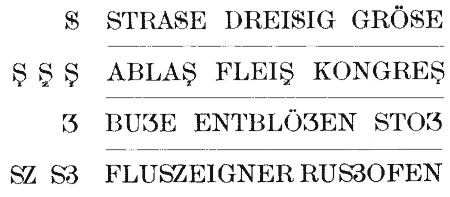
[Mitglied b750…] Geschrieben März 8, 2003 Teilen Geschrieben März 8, 2003 Folgendes erreichte mich per Mail. Ich denke, das ist ein interessanten Diskussionsthema, das vielleicht auch andere interessiert: Hallo Herr Herrmann, ich habe vor einiger Zeit ihr Typotutorial über die richtige Verwendung des Eszett gelesen und es sprach mir geradezu aus der Seele. Leider entdecke ich sehr oft peinliche ß-Fehler im Alltag. Vor einigen Monaten erblickte ich im Supermarkt den Grießpudding eines regionalen Milchproduktherstellers. Die Verpackung war durchaus schön gestaltet, doch war das Wort Grießpudding komplett in Versalien gesetzt mit einem ß an fünfter Stelle! Zu Hause angekommen schrieb ich der Marketingabteilung des Unternehmens eine ausführliche Mail mit Verweis auf den relevanten Absatz im Duden. Einige Wochen später erhielt ich zu meiner eigenen Verwunderung tatsächlich eine Antwort. Die verantwortliche Dame erklärte mir, dass sie dies Problem ausführlich intern diskutiert habe und dabei auch auf weitere Fehler auf den Produktverpackungen ihres Hauses aufmerksam wurde. Jedoch wäre eine sofortige Korrektur der Verpackungen aus Kostengründen leider nicht zu realisieren. Am Ende dankte sie mir für meine Aufmerksamkeit und war erstmal zufrieden … mal schauen wie lange die Änderung der Verpackung auf sich warten lässt. :) Durch Zufall stieß ich letztens auf einen alten DDR-Duden aus dem Jahre 1962, auf dessen Titel folgendes zu lesen ist: »DER GROßE DUDEN RECHTSCHREIBUNG«. Ich war für einige Sekunden absolut sprachlos und habe sogleich ein Beweisfoto geschossen und an diese Mail angehängt. Vielleicht lässt sich ja mit ein wenig Aufwand die Ursache für diesen peinlichen Faux Pas ausfindig machen … Im Kapitel »Rechtschreibung der Laute« steht zum Thema Eszett u.a. folgendes: »Das Zeichen ß fehlt leider noch als Großbuchstabe. Bemühungen, es zu schaffen, sind im Gange. Es wird jetzt noch ersetzt durch SS oder, falls Mißverständnisse möglich sind, durch SZ.« Ist die Frage warum es auf dem Titel dann defitiv falsch geschrieben ist. Gab es tatsächlich Bemühungen eine Ligatur für die Versalien zu schaffen? Als ich das las, war ich sehr fasziniert von dem Gedanken eines großen Eszetts. Ich werde versuchen mich im neuen Semester meines Designstudiums dem Thema anzunehmen, mal schauen was mein Typo-Prof. zum Thema sagt. Zum einen möchte ich herausfinden ob es tatsächlich Bemühungen dieses Art gab, wenn ja wie weit sie fortgeschritten waren und warum bis heute keine Ligatur der Versalien S und Z existiert. Zudem würde ich gern eigene Gestaltungsmöglichkeiten großer Eszetts bekannter Schriften kreieren. Ich würde mich sehr über eine Antwort von Ihnen freuen! Viele Grüße! Martin Jordan Link zu diesem Kommentar
[Mitglied b750…] Geschrieben März 8, 2003 Teilen Geschrieben März 8, 2003 Dass es Bemühungen gab, ein "großes Eszett" zu etablieren, ist mir auch neu. Aber mag ja sein, dass es in der DDR diese Bemühungen gab, diese dann aber mit der Wende nicht weiter verfolgt wurden. Schließlich gibt es ja auch keinen "DDR-Duden" mehr. Aber wozu brauchen wir ein großes Eszett? In der deutschen Rechtschreibung gibt es kein einziges Wort, das mit einem Eszett beginnt. Also gibt es auch keine Notwendigkeit für ein großes Eszett. Und nur für den Versalsatz ein solches zu schaffen? Ich finde es falsch, einen Buchstaben in unser Alphabet einzusetzen, wenn es dafür keine rechtschreiberische Notwendigkeit gibt oder wenn er nur in Ausnahmen eingesetzt wird (und der Versalsatz ist ja eine typografische Ausnahme, die man nur in Überschriften und Hervorhebungen einsetzt). Wenn jemand gerne ausschließlich Versalien verwenden möchte und ein Eszett drin vorkommt, muss er sich halt mit einem Doppel-S behelfen. Das ist ja auch keine Katastrophe. Denis Link zu diesem Kommentar
[Mitglied b750…] Geschrieben März 10, 2003 Teilen Geschrieben März 10, 2003 Meines Wissens ist das "ß" kein Buchstabe, sondern eine Ligatur aus "s" und "z" und kann somit schwerlich ... äh ... kapitalisiert werden. Nicht, dass es unmöglich wäre, aber nicht ganz einfach, sicherlich. :) http://www.carb.de Link zu diesem Kommentar
[Mitglied b750…] Geschrieben März 10, 2003 Teilen Geschrieben März 10, 2003 Sicher ist das Eszett eine Ligatur aus zwei Kleinbuchstaben. Aber es existieren doch durchaus auch Ligaturen bestehend aus zwei Versalbuchstaben. Was spricht also dagegen im Rahmen eines Semesterprojekts einfach mal nach jenen alten Entwürfen zu recherchieren und dann ein wenig zu experimentieren? Es werden meiner Meinung nach weitaus sinnlosere Projekte an unseren Hochschulen für Gestaltung durchgeführt und unterstützt … dass das dabei eventuell herauskommende Zeichen NICHT von der Öffentlichkeit als großes Eszett akzeptiert wird und am Ende zum Einsatz kommt ist mir durchaus klar. Dennoch bin ich einfach unglaublich neugierig, was dort vor 40 Jahren in Köpfen der ostdeutschen Typographen ausgedacht worden ist. Vielleicht sind ja sehr spannende Ansätze für die Kreation ein komplett neues Buchstabens dabei … vielleicht sind aber die Ideen auch längst mit ihren Schöpfern begraben. Ich möchte es herausfinden … für mich. Gruß. Martin Jordan. Link zu diesem Kommentar
[Mitglied b750…] Geschrieben März 10, 2003 Teilen Geschrieben März 10, 2003 Zugegebenermasen kann man in der Praxis nur ab und zu was mit einem versal ß anfangen. Allerdings wäre es echt sinnvoll damit endlich das "ß" aus Versalheadlines verschwindet. Wie wäre es mit einem Wettbewerb: Gestaltung eines versal "ß". Die besten 3 werden dann dem Duden zugesandt. Gruß Jens PS: falls du das Buch Schriftkunst von Kapr hast schau mal ob er was dazu sagt. Leider lebt er nicht mehr. Ansonsten könntest du mal versuchen Hans Peter Willberg zu fragen oder irgend einen anderen Link zu diesem Kommentar
[Mitglied b750…] Geschrieben März 12, 2003 Teilen Geschrieben März 12, 2003 Hallo Martin da mich dieses Thema auch selber sehr reizt hab ich mal ein paar Bücher gewälzt. Leider läst sich rein oberflächlich nicht viel herausfinden. Erst gestern abend hab ich noch mal in Schriftkunst geschaut. Doch leider hab ich das Thema ß auch nicht mehr gefunden. Bin aber sicher das da was drin stand. Er führt nähmlich die Entstehung auch auf langes s und z zurück. Dann aber im Buch Detailtypografie auf Seite 240: <blockquote>Alle Versuche zur Bildung einer Versal SS-Ligatur sind im Sande verlaufen. Es ist weder nötig nochschön, statt desen SZ zu setzen...</blockquote> Das Beweist auf jeden Fall das es solche Bemühungen definitiev gegeben hat. Auf Seite 194 stand noch: <blockquote>Das ß ist übrigens keine Zusammenziehung aus dem langen s und dem Schluß-s! (siehe Herbert E. Brekle: Zur handschriftlichen und typographischen Geschichte der Buchstabenligatur ß ..., im Gutenberg-Jahrbuch 2001, S.67)</blockquote> Hat das jemand gelesen? Gruß Jens Link zu diesem Kommentar
[Mitglied b750…] Geschrieben März 12, 2003 Teilen Geschrieben März 12, 2003 Wenn man wirklich eine Versalvariante der Ligatur ß gestalten möchte, müsste diese ja auch eine Ligatur sein. Geht man aber davon aus, dass das ß eine Ligatur aus langem s und z bzw. Schluss-s ist, müsste man ja erst mal eine Versalfassung des langen s gestalten. Denn das gibt's ja auch nur als Kleinbuchstabe. Und nun? Denis Link zu diesem Kommentar
[Mitglied b750…] Geschrieben März 14, 2003 Teilen Geschrieben März 14, 2003 Ungeachtet des Sinnes geht die Suche für mich weiter. Falls dich also noch interessiert Martin hab ich da noch drei Statements gelesen: http://www.kaube-becher.de/html/s.html geht auf das "S" im allgemeinen ein. Dort steht unteranderem: Übrigens leisteten die Deutschen einen eigenen Beitrag zur Geschichte des "S". Im 14. Jahrhundert erfand ein heute unbekannter Grammatiker einen neuen Buchstaben, den er aus einem "S" und einem "Z" zusammensetzte: das "Eszet". Diese Neuheit sollte als scharfes "S" ("ß") dienen, weil es so einen Laut damals in der deutschen Sprache nicht gab. Seit 600 Jahren beweist dieser Buchstabe seine Nützlichkeit. Erst jetzt im Informationszeitalter scheint er zum Hindernis zu werden. Das weiß jeder, der schon einmal ein "ß" in einer Botschaft im Netzwerk geschrieben hat. Es kommt nicht als "ß" an, sondern als irgendein beliebiges Zeichen. Der Cyberspace versteht eben nur das ursprüngliche lateinische Alphabet. Leider weis ich nicht ob diese Aussage anerkannt ist. An andere Stelle las ich noch http://www.uni-bamberg.de/ggeo/hilfswis ... rten2.html Auch ß ist ursprünglich eine Ligatur aus einem s in der Langform und einem Rund - s. sz ist eine völlig ahistorische, nur am Erscheinungsbild und nicht an der Genese orientierte Bezeichnung. Scheint etwas wiedersprüchlich zu Detailtypografie zu sein. Zuletzt las ich noch in einem PDF (in Fraktur gesetzt): http://omega.enstb.org/yannis/pdf/dante2000.pdf Für ß wird in großer Schrift SZ angewandt, z. B. MASZE (Maße) — aber MASSE (Masse) —, STRASZE, PREUSZEN, MEISZNER, VOSZ. Die Verwendung z w e i e r Buchaben für e i n e n Laut ist nur ein Notbehelf, der aufhören muß, sobald ein geeigneter Drucbuchstabe für das große ß geschaffen ist. Allerdings ist mir noch ein Gedanken warum eine Versalligatur aus SS in der deutschen Sprache gibt. Es ist durchaus möglich das dies an der historischen Vergangenheit liegt. Gruß Jens Link zu diesem Kommentar
[Mitglied b750…] Geschrieben April 27, 2003 Teilen Geschrieben April 27, 2003 In einer französichen Handschrift von 1608 habe ich eine Ligatur aus langem und kurzem s gesehen, die 100% für einen Deutschen wie ß ausschaut. Im gleichen Text wurde ebenfalls die "normale" lang s, lang s Ligatur verwendet. Beide nicht am Wortende. Kann sein, daß es nur eine Spielerei war. (... le fondement asseuré de la noblesse.) asseuré - doppel lang s Ligatur noblesse - lang s, kurz s Ligatur, wie ß Link zu diesem Kommentar
[Mitglied b750…] Geschrieben Dezember 1, 2003 Teilen Geschrieben Dezember 1, 2003 Obwohl das Thema nun bereits einige Monate alt ist, lässt es mich nicht mehr los. Derweil hab ich nun der hervorragenden Ausbildung im Bereich Schrift wegen an die FH Potsdam angewechselt, wo ich u.a. bei Betina Müller »Typografie« und im kommenden Semester bei Lucas de Groot »Schriftentwicklung« studiere. Durch Zufall kam ich letztens im Gespräch mit Prof. Müller auf den »falschen Duden« und die Geschichte mit dem großen ß. Sie hat wiederum durch den Dozenten im Fach »Kalligrafie«, Hans-Jürgen Willuhn, der in der ehemaligen DDR als Gebrauchsgrafiker tätig war und scheinbar gute Kontakte zu den Leipziger Typografen hat, die damaligen ß-Entwürfe gesehen und wird sie mir Ende der Woche mitbringen … sie sprach von sehr spannenden Arbeiten diverser Osttypografen und einem abrupten Stopp des Projekts aufgrund von internen Differenzen unter den beteiligten Gestaltern. Ich bin äußerst gespannt und halte Euch auf dem Laufenden! :) :: geändert von MartinJordan [ 1/Dec/2003 08:57 PM ] :: Link zu diesem Kommentar
[Mitglied b750…] Geschrieben März 17, 2004 Teilen Geschrieben März 17, 2004 »Das Zeichen ß fehlt leider noch als Großbuchstabe. Bemühungen, es zu schaffen, sind im Gange.« ist im Leipziger Duden von 1962 zu lesen und Dank Hans-Jürger Willuhn kann ich die Entwürfe des Wettbewerbs in den frühen 60er Jahren hier posten. Wie Herr Willuhn meinte wurden die Bemühungen von politischer Seite aus gestoppt – aus welchem Grund ist nicht klar. <img src=http://www.martinjordan.de/Studium/Eszett.jpg> Link zu diesem Kommentar
Ralf Herrmann Geschrieben März 12, 2005 Teilen Geschrieben März 12, 2005 Wichtig wäre aber endlich heute einen Großbuchstaben ß zu schaffen, der sich aus langem s und Schluß s herleitet, weil das ß heute nur in diesem Zusammenhang benutzt wird, und da würde ein sz Verschmelzung nur verwirren. Andreas Stötzner hat sich intensiv mit diesem Thema beschäftigt und dem Unicode-Konsortium sogar einen entsprechenden Vorschlag unterbreitet, der sich hier http://std.dkuug.dk/jtc1/sc2/wg2/docs/n2888.pdf in voller Breite studieren lässt. (Soweit ich weiß, ist der Versuch aber bislang erfolglos geblieben ...) Ralf 1 Link zu diesem Kommentar